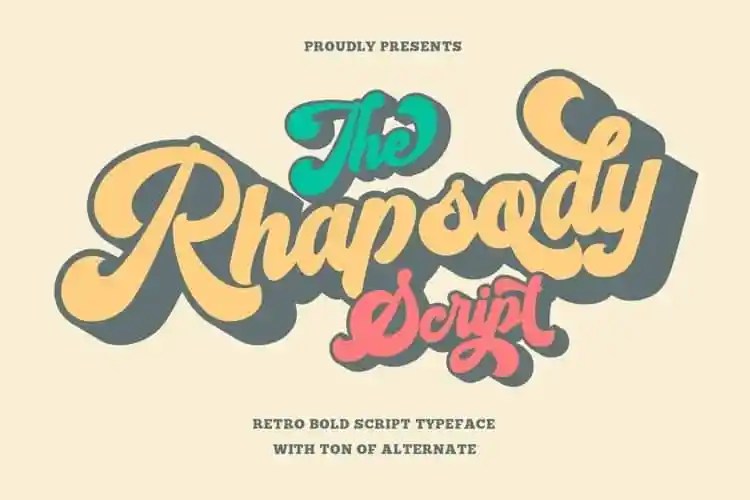
A fonte Rhapsody Script é uma escolha perfeita para aqueles que buscam estilo vintage e moderno. Inspirada nos gatilhos tipográficos retro dos anos 70 e 80, esta font faz um equilíbrio entre letras limpas e suaves e um estilo bold que se assemelha a desenhos de letras na década de 1970. Desenvolvida por um designer conhecido como Bluetype, essa fonte é uma excelente escolha para quem precisa de estilos vintage em suas logomarcas, camisetas, selos vintage, branding retro, citações e embalagens. Seja você um designer gráfico ou criador de conteúdo digital que busca trazer um toque nostálgico a seus projetos, Rhapsody Script é uma ótima escolha para deixar seu design com aquele charme retro único e contemporâneo.